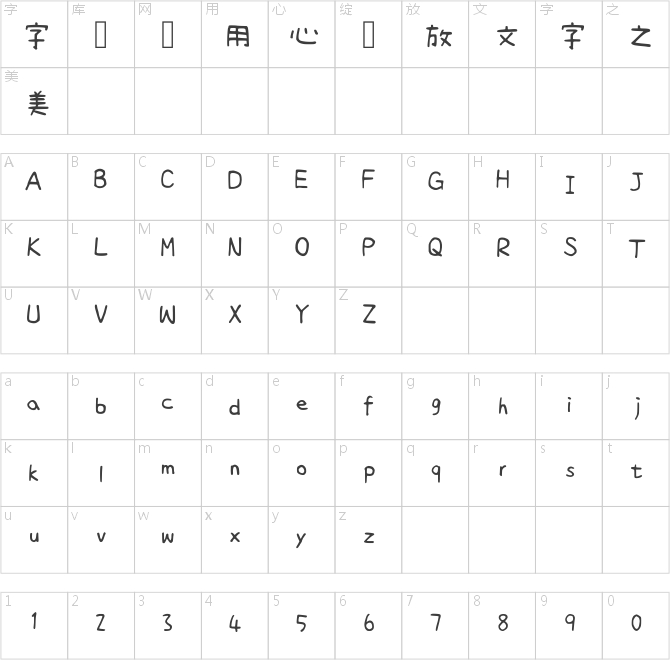
字体名称: 清松手寫體3
清松手寫體3
清松手寫體3介绍
清松手写体是游清松在稿纸上用原子笔手写,透过“守写字”网站产生出初稿字型档,再字体软件制作加工而成的手写字型。
清松手写体手写字型,没有一般电脑字型的生硬感,多了几分手写般的自然感。不论是中文、英文、符号数字,适合在电脑屏幕上阅读、排版、打印出来效果也很棒!
清松手寫體3字体清松手写体3字库是一款让人赏心悦目、百看不厌的中文字体,适合各类广告和产品包装设计应用,字体大小3.45MB,格式为ttf字体,上传用户是KISEKI,作者/版权方为游清松